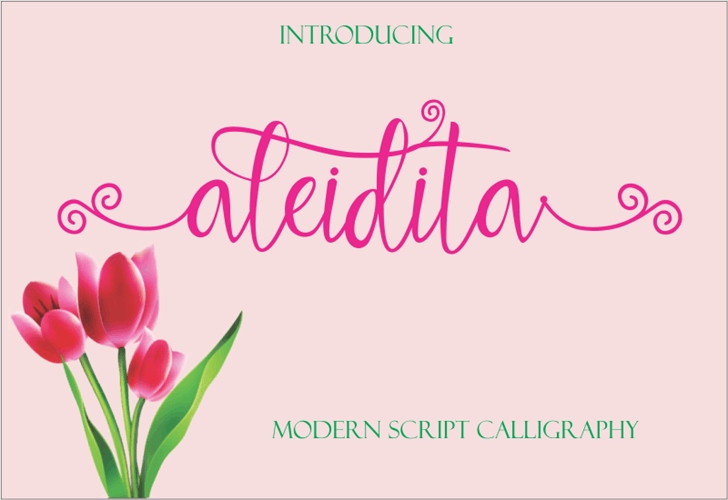
Aleidita Script Font – Download Grátis
Introduzimos Aleidita Script, uma elegante tipografia script com traços fluidos. Esta fonte foi criada por Jaime Rangel Castro e é compartilhada para diferentes usos. Suas linhas curvas podem ser utilizadas de diversas maneiras: como título em um design, assinatura personalizada, logomarca, correspondência familiar, convites de casamento, cartões de visita, sinalização, rótulos, newsletters, material publicitário, selos e até mesmo adesivos. Estamos ansiosos para que você descubra as inúmeras maneiras em que pode usar Aleidita Script para enriquecer seu design.